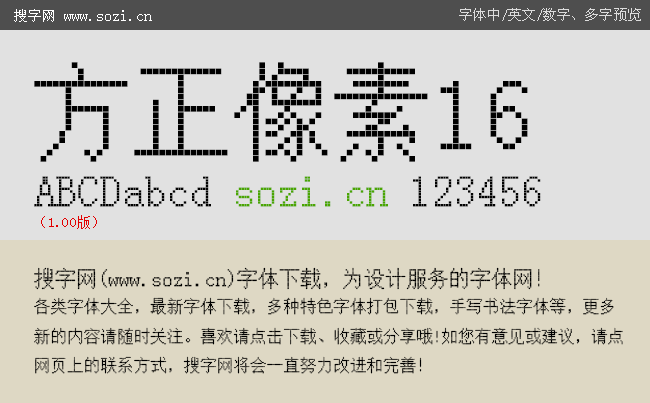
方正像素16
搜字網(wǎng)提供一款方正像素16中文字體下載,方正像素字體由正方形像素點(diǎn)組成的基于黑體、宋體基本字形的一套字體系列。方正像素體具有規(guī)范、工整,容易辨認(rèn)的特點(diǎn),適用于LED屏等電子屏幕,在易識的同時(shí),體現(xiàn)科技感和現(xiàn)代感。適合書籍設(shè)計(jì)、展板設(shè)計(jì)、海報(bào)設(shè)計(jì)等廣告設(shè)計(jì)場合使用。